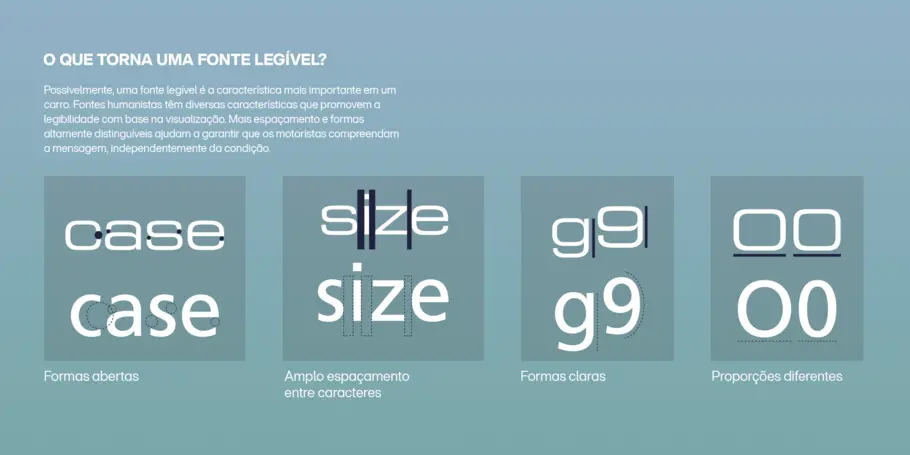
As fontes de ficção científica funcionam no futuro real?
Em um episódio recente de Creative Characters, nosso podcast, o anfitrião e diretor criativo de tipografia da Monotype Terrance Weinzierl conversou com o designer e pesquisador Dave Addey sobre como os futuros que imaginamos nem sempre são práticos para as realidades em que vivemos – através da lente do design dos filmes de ficção científica.
Como exemplo, Dave fala sobre as telas transparentes de Minority Report e outros filmes, que parecem impressionantes em nosso imaginário, mas seriam um pesadelo de legibilidade na vida real.
“Como designers, acredito que precisamos ter um pouco de cautela”, aponta Dave, “com os designs que vemos em filmes de ficção científica e que podem parecer incríveis e inspiradores, mas que na prática estão longe de serem ideais.”
Algumas das fontes que os cineastas usam para evocar o futuro na verdade não funcionam em situações da vida real tampouco. Terrance e Dave discutem como certas fontes de ficção científica, especialmente a Eurostile Next, foram amplamente usadas em mostradores de carro nos anos 80 e 90 graças aos seu formato de letra que combinava com a forma do carro – e não necessariamente porque elas eram as mais legíveis para o painel.
Há vários anos, a Monotype realmente se associou ao Instituto de Tecnologia de Massachusetts (MIT) para testar se a Eurostile Next era uma boa escolha para os mostradores de carro. A pesquisa explorou o impacto da tipografia e das escolhas de design na legibilidade em mostradores ou painéis de carro. Realizamos um experimento de simulação de direção em um carro com tecnologia de rastreamento ocular e pudemos explorar os efeitos que a escolha da fonte tem enquanto é olhada e no tempo de resposta através de diversas variáveis. Testamos diversos fatores de design intrínsecos e extrínsecos, como cor (texto preto em fundo branco e vice-versa), estilo de fonte, tamanho do texto, além dos atributos tipográficos de dois tipos diferentes, a Frutiger e a Eurostile.
Não muito adequado para a estrada.
Por meio desta série de estudos, pudemos concluir que escolher uma fonte com certas características pode otimizar a aparência de uma interface homem-máquina (IHM) automotiva e reduzir o tempo de visualização para os motoristas. Frutiger, uma tipografia humanista com formas abertas, espaçamento entre caracteres amplo e formas inconfundíveis, foi considerada mais legível do que a grotesca e quadrada Eurostile.